もじもじでは、子どもたちが課題を自分で選びます。
「今日はこれを書きたい」と、自分の気持ちで決めるところからスタートします。
その課題の中に、最近新しく加えた言葉があります。
「飛躍」と「挑戦」です。
どちらも、字の形としても少し難しさがあり、意味としても力強い言葉です。
うまく書けそうな字を選びたくなる気持ちも、もちろん自然なこと。でも、少し「難しそうだな」と感じる文字に向き合う時間も、実はとても大切だと私は感じています。
今日は、その新しい課題字について少しご紹介しますね。
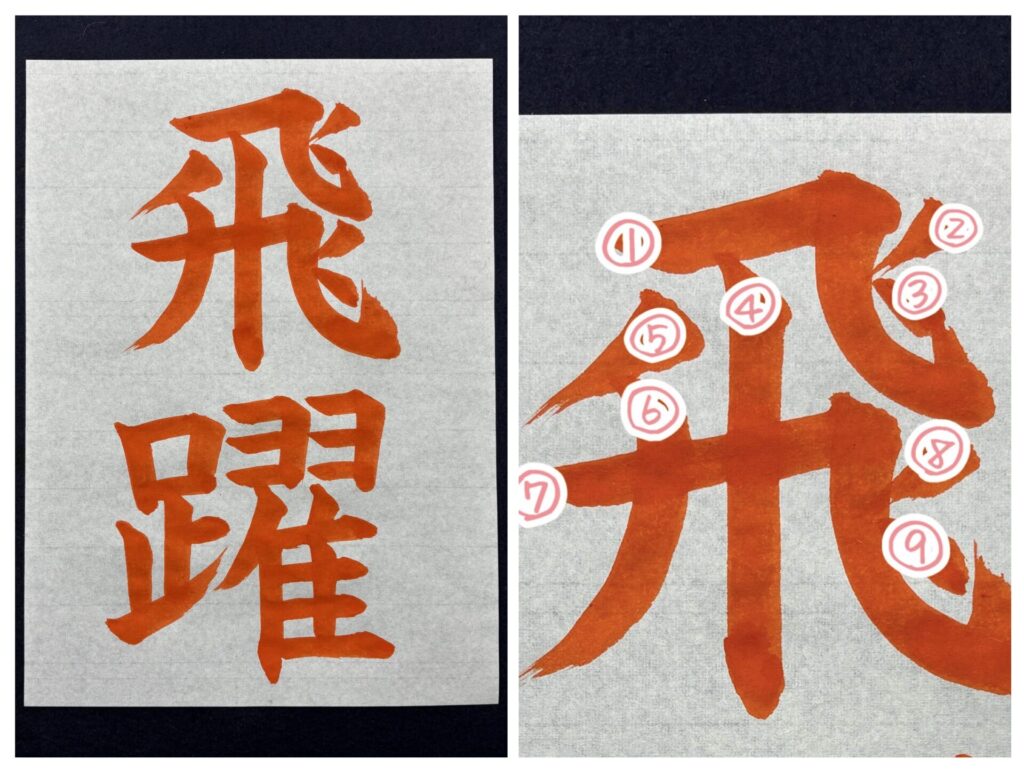
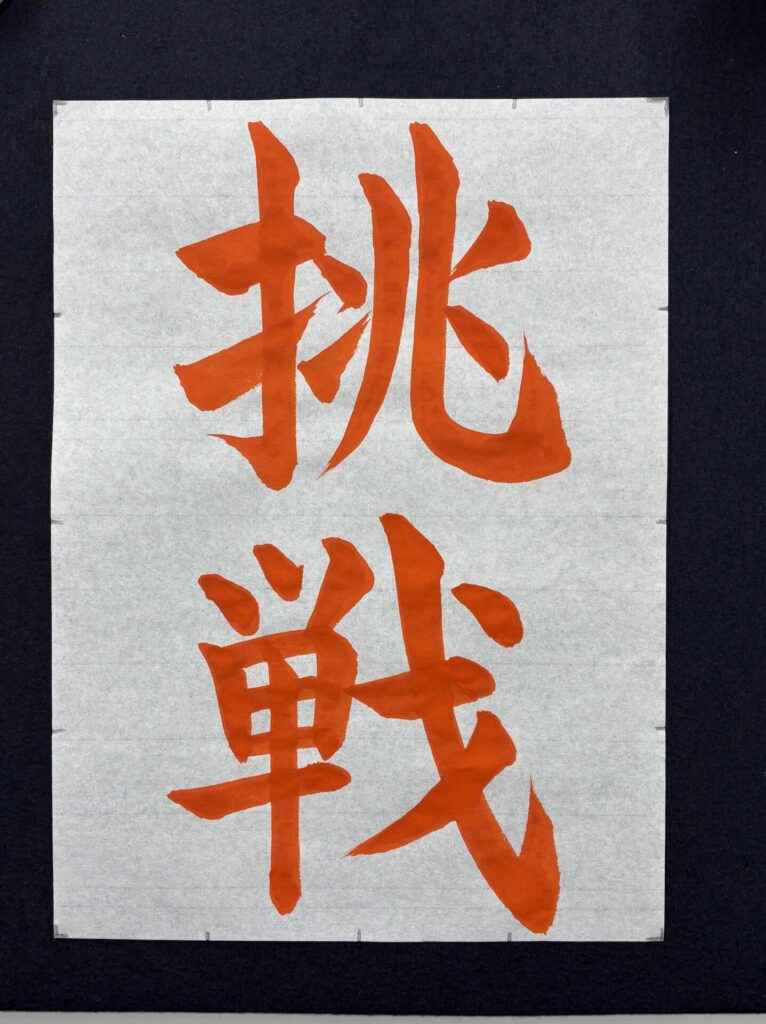
「飛躍」のポイント ー 「飛」の書き順に注意
「飛躍」の中でも、子どもたちが戸惑いやすいのが「飛」の字です。
画数も多く、形も複雑。
どこからどう書き始めるのか、迷いやすい文字です。
特に大切なのは書き順です。
「飛」は、順番を守ることで線の重なりが自然になり、全体の形が安定します。
逆に、自己流で書いてしまうと、左右のバランスが崩れたり、線がちぐはぐに見えたりします。
書き順はただの“約束”ではなく、形を整えるための工夫なのだと、練習を通して実感していきます。
「挑戦」のポイント ー 「戦」の“ほこづくり”
そしてもう一つの課題字が「挑戦」です。
この言葉を、5年生の子が自分で選びました。
「戦」の字の右側は、“ほこづくり”と呼ばれる部分。
斜めに少しそらす動きと、最後のはねがポイントになります。
ここがまっすぐになってしまうと、字がかたく見えてしまいます。
少しだけ角度をつけてそらすことで、形に動きが生まれます。
最初はうまくいかなくても、何度も書くうちに少しずつ感覚をつかんでいきます。
課題は「自分で選ぶ」から意味がある
もじもじでは、課題を自分で選びます。
うまく書けそうな文字を選ぶことも大切です。
一方で、少し難しそうな言葉に挑戦する時間も、確実に力になります。
今回追加した「飛躍」と「挑戦」は、
・書き順を丁寧に確認すること
・点画の角度やはねを意識すること
といった基礎を改めて見直せる課題です。
技術面の練習でありながら、
「どの課題を選ぶか」という判断もまた、大切な学びの一つです。
これからも、子どもたちが自分で選び、
その中で少しずつ難易度を上げていけるような課題を増やしていきたいと思います。